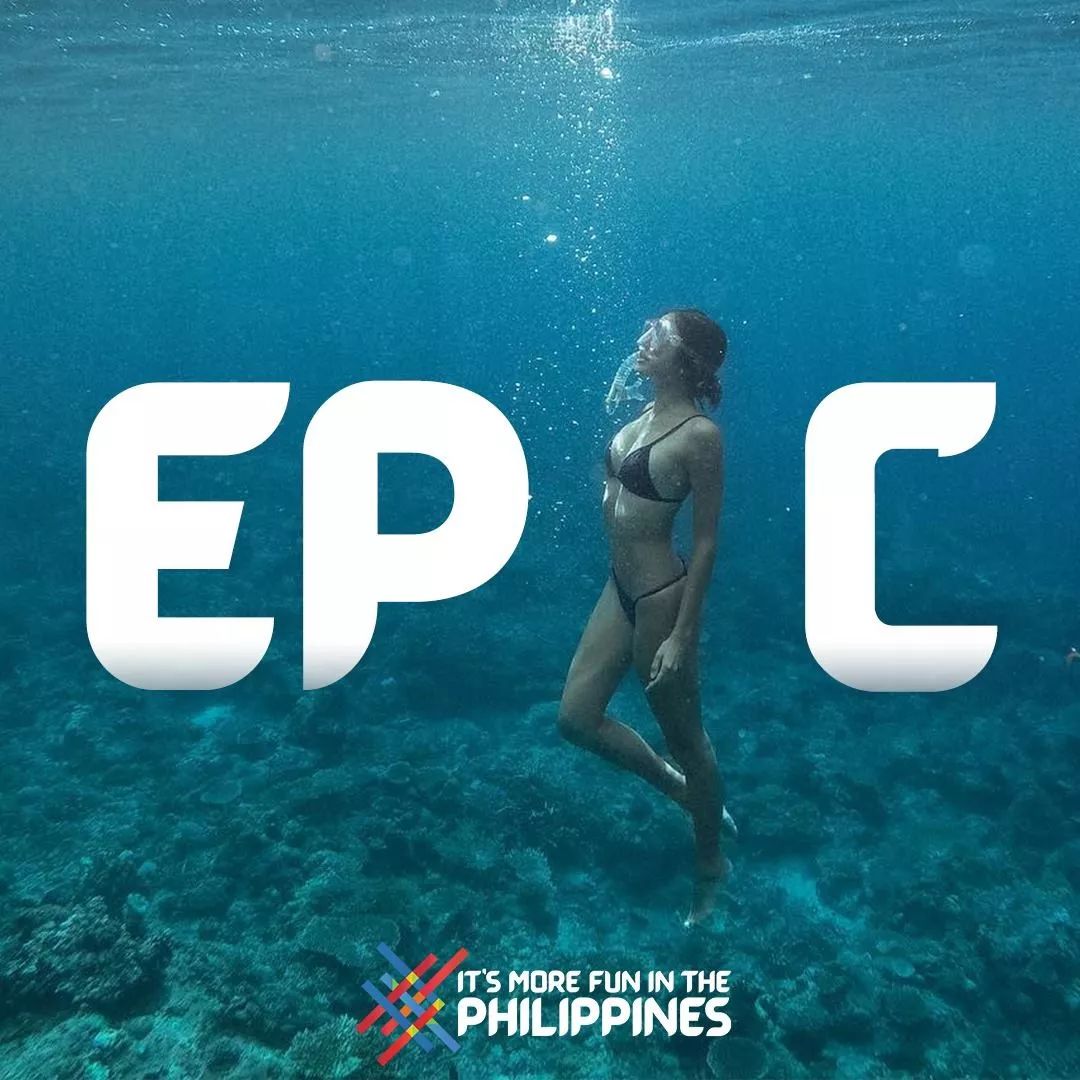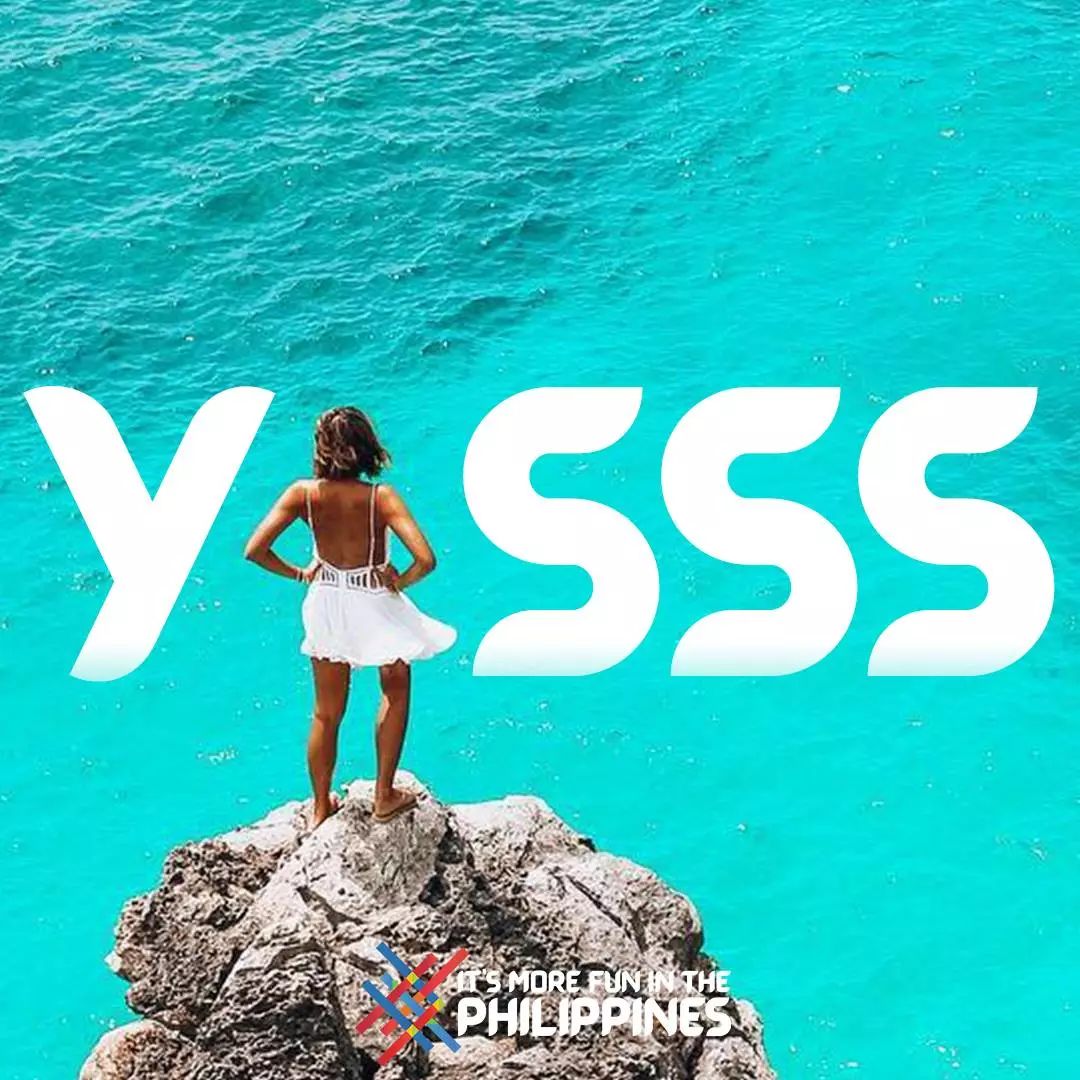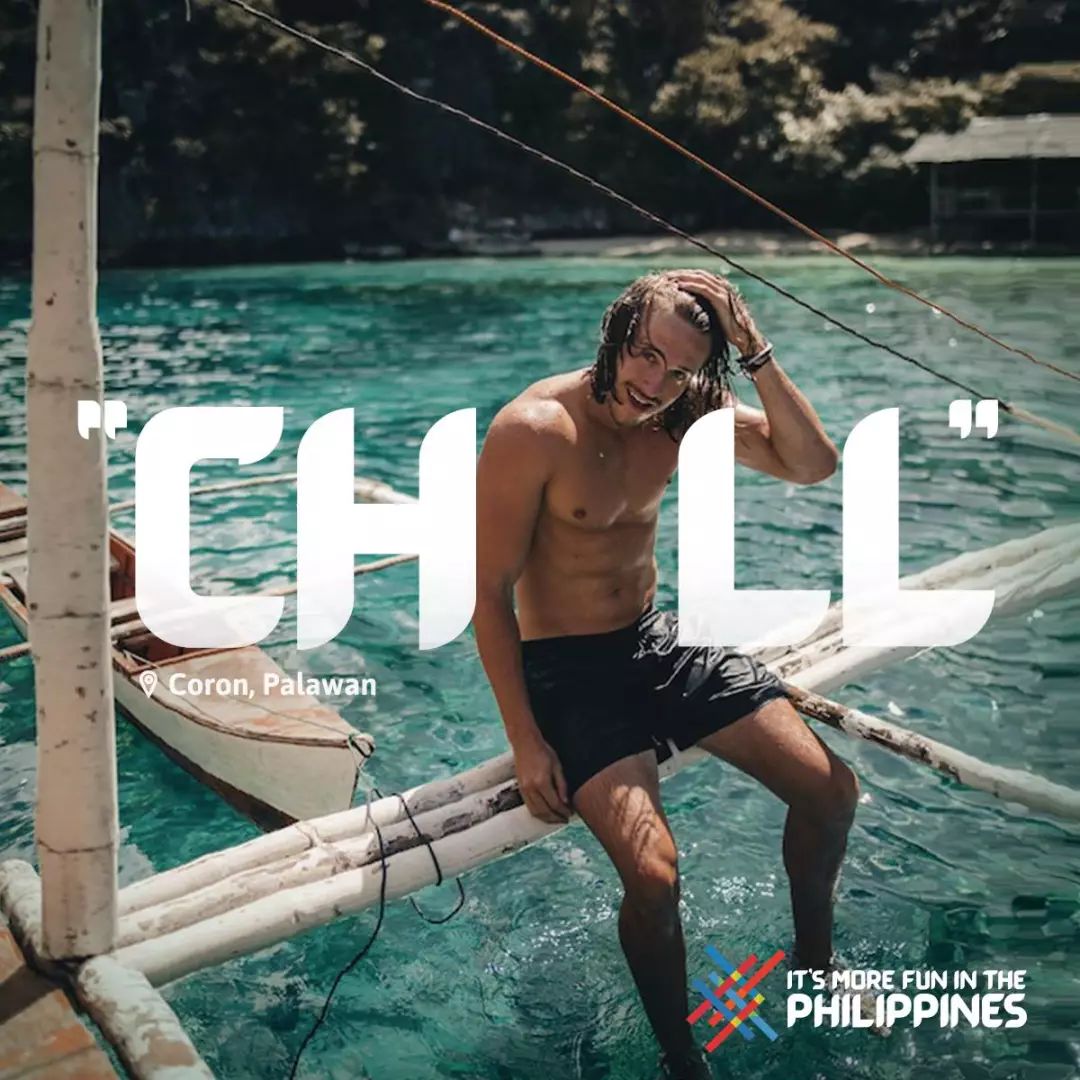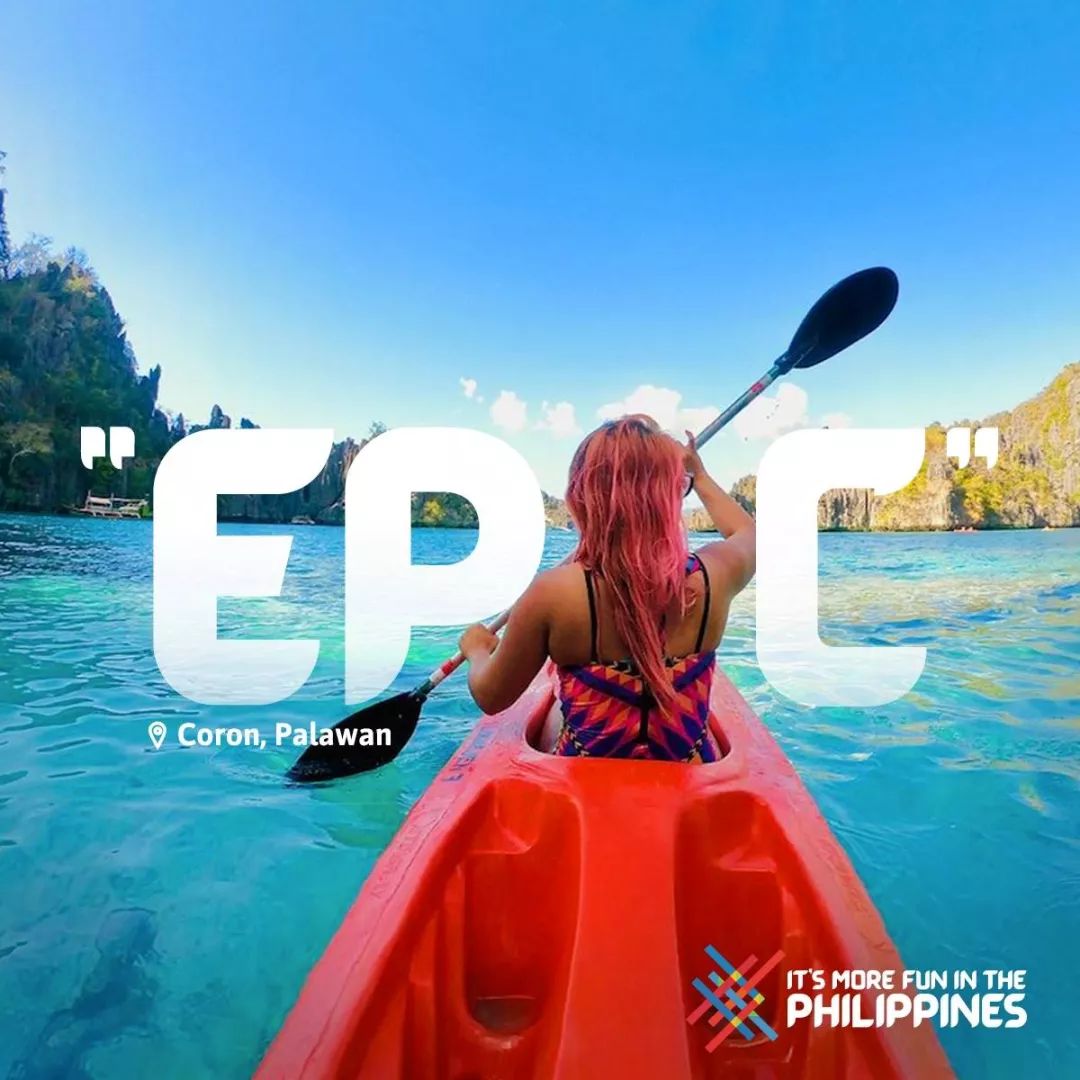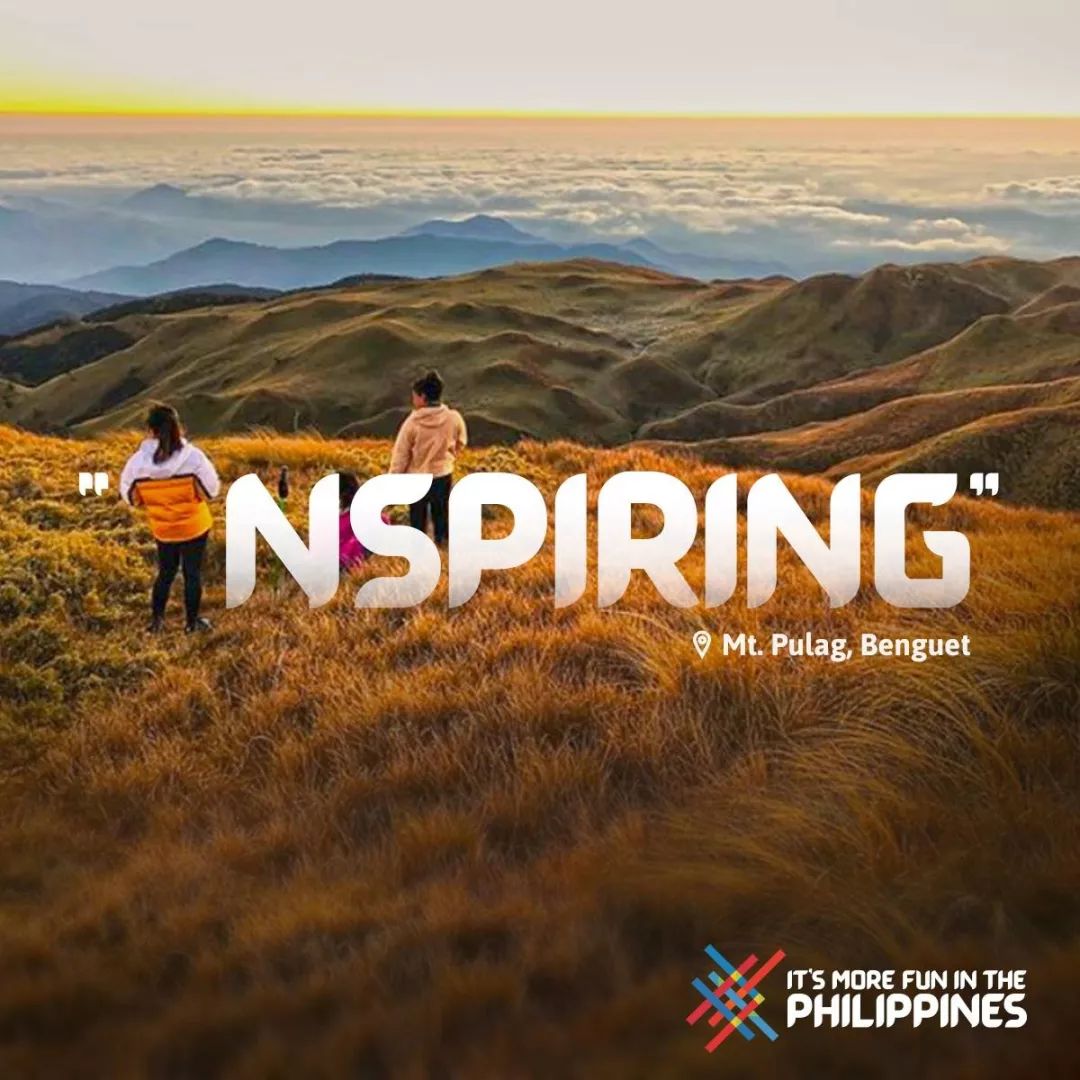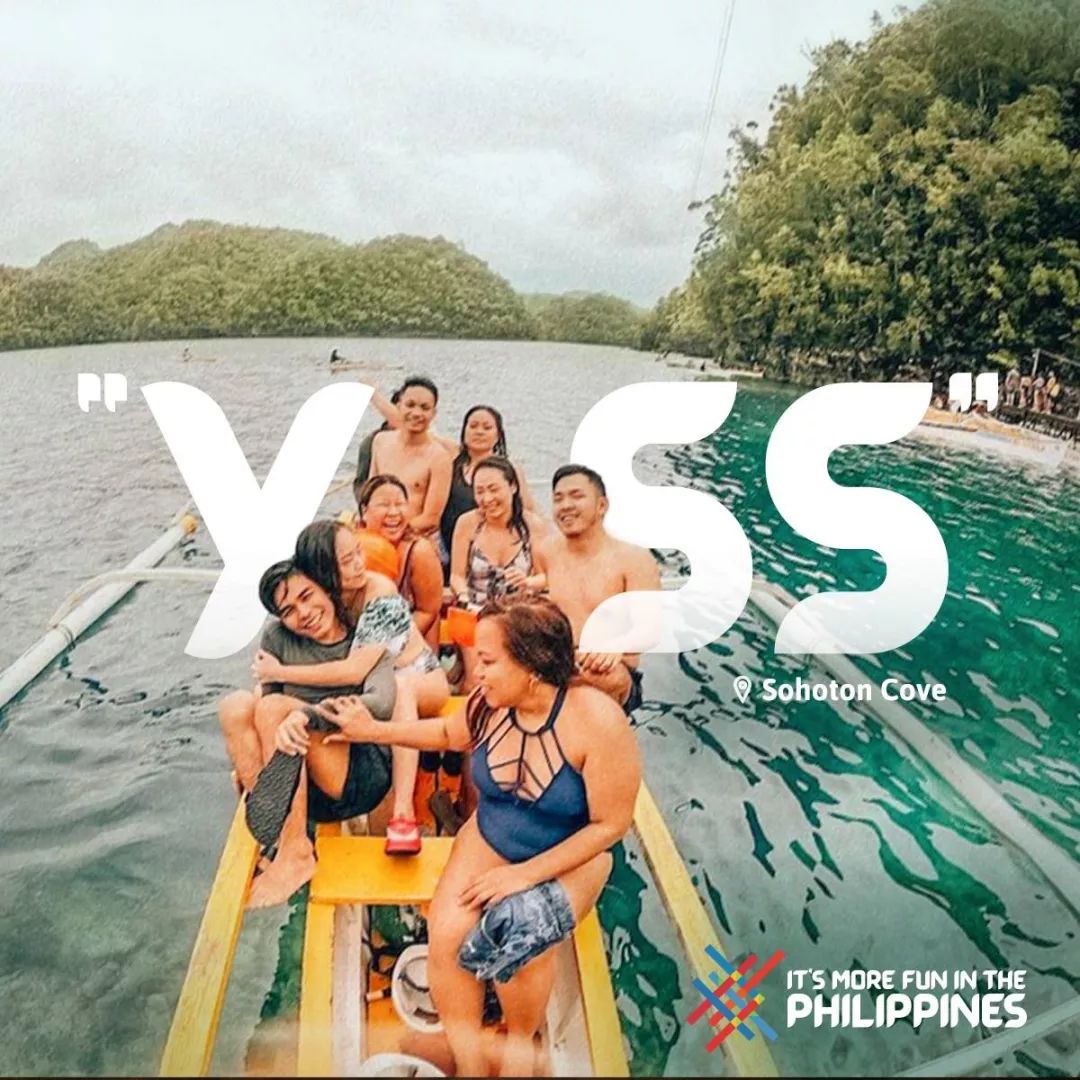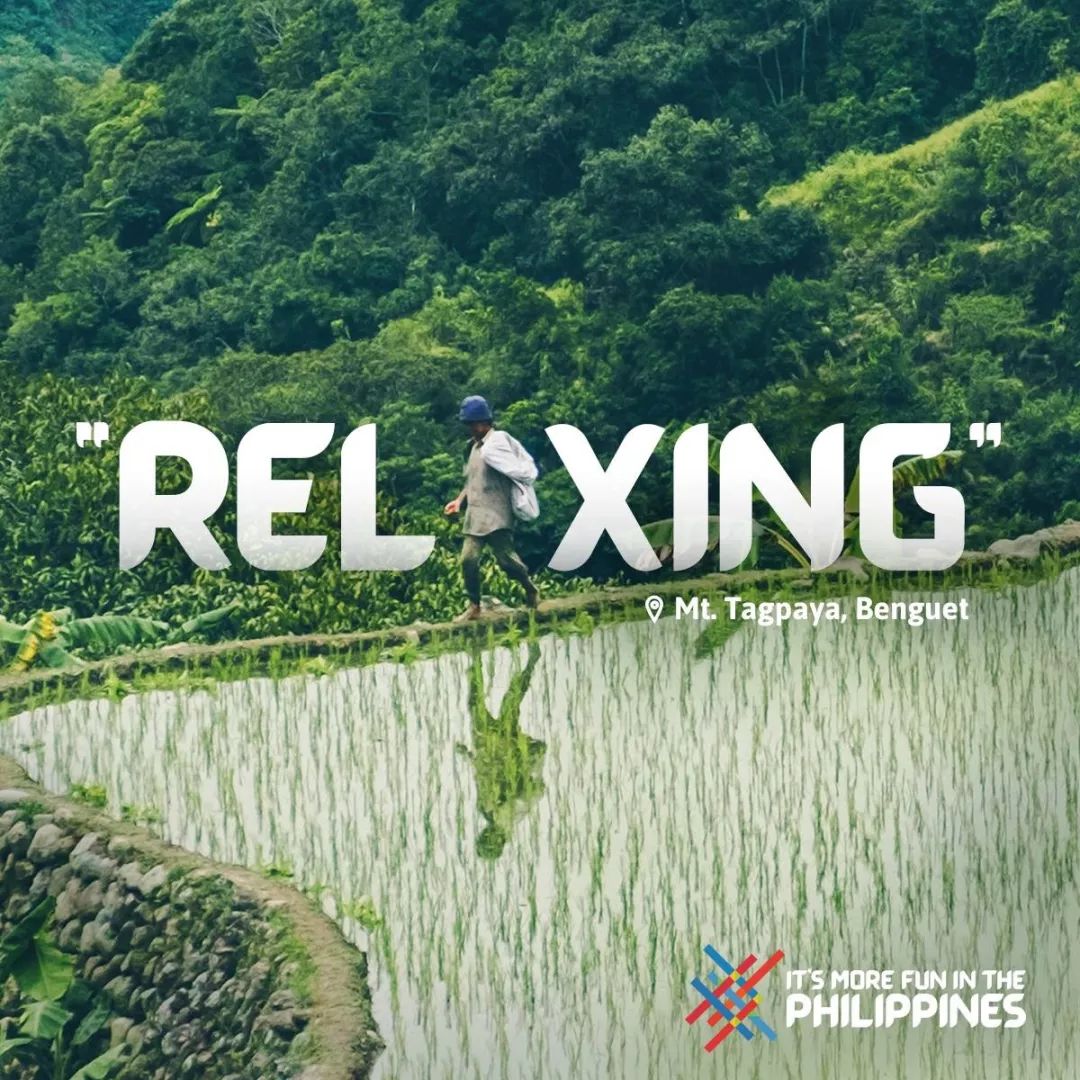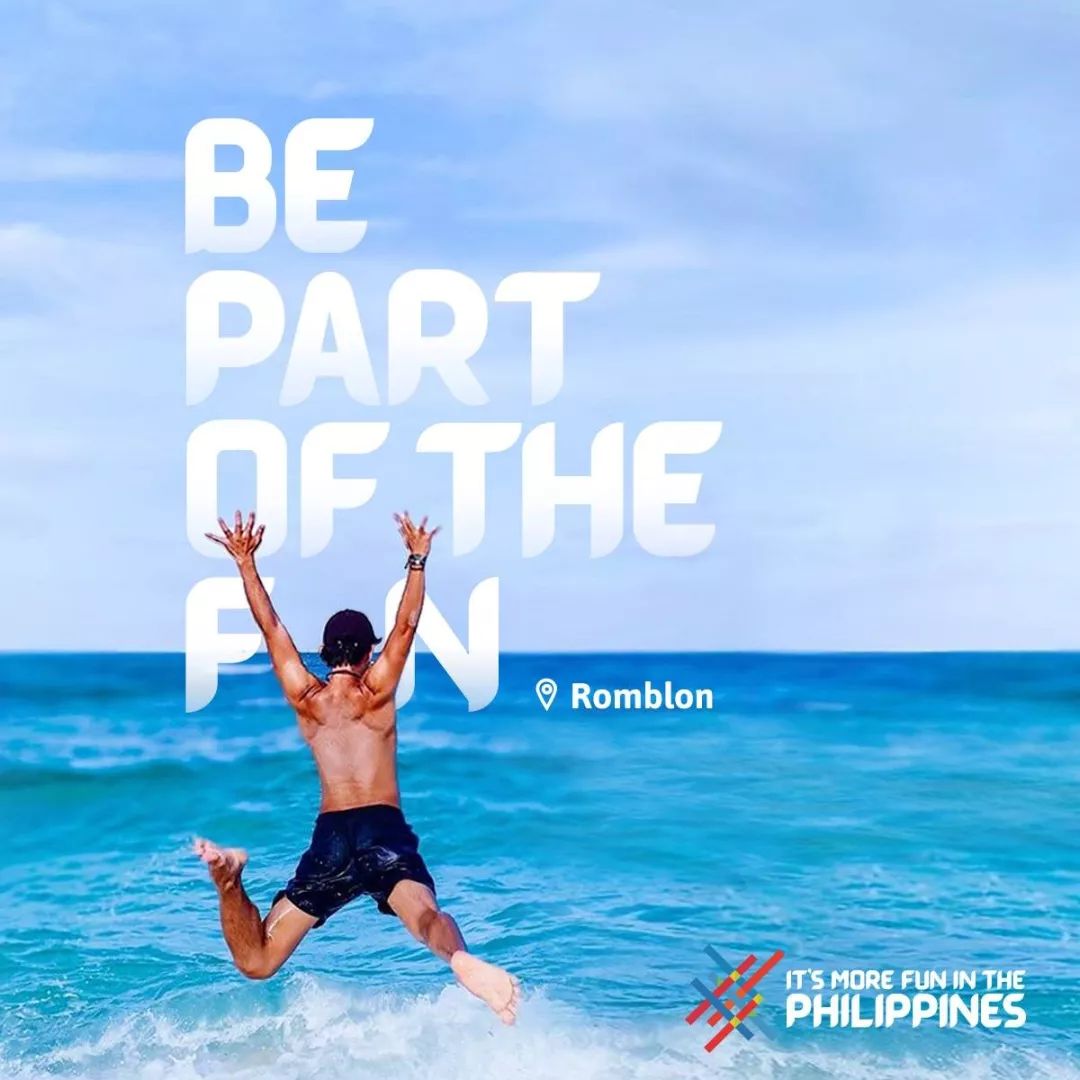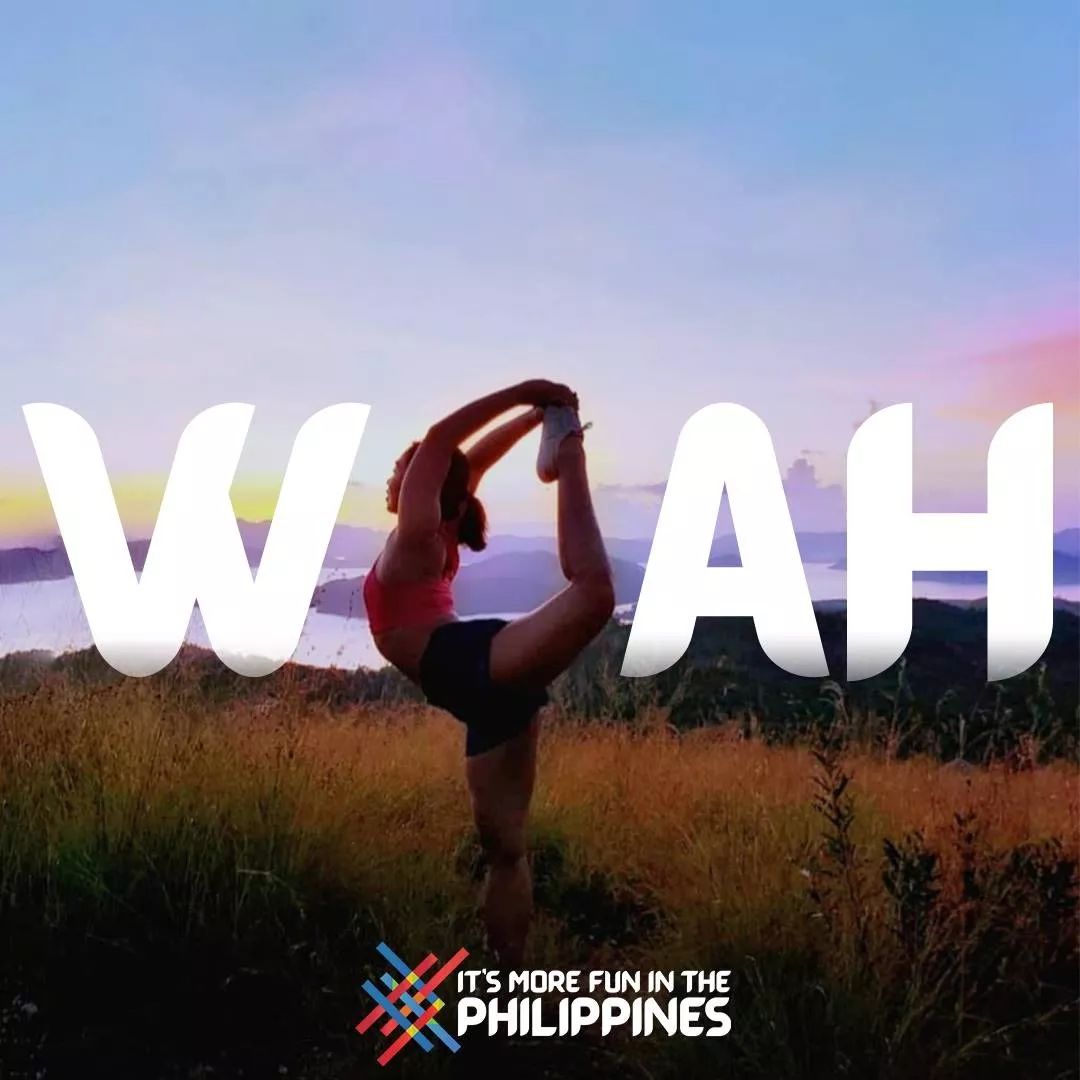
她设计了一套定制字体,让全球500万网友免费宣传!
“菲律宾更有趣!”(It’s More Fun in the Philippines)是2012年4月在菲律宾一次旅游活动中推出的新口号。
2019年2月18日,菲律宾旅游部(DOT)宣布重启“菲律宾更有趣!”这一口号,并采用了全新的LOGO。
新LOGO延续使用传统色彩和图案,并在原有的基础上进行了简化。新的配色取材于菲律宾传统编织、海洋、阳光、大梯田。
“菲律宾更有趣!”既是菲律宾的旅游品牌,同时也是一个应用程序,鼓励游客们发现菲律宾之美:游客在拍摄照片后与活动口号“菲律宾更有趣”定制叠加后,分享到Facebook、Instagram、Twitter等社交媒体。
此次品牌重塑,最明显的变化之一是广告中的新字体——一套名为“Barabara”的定制字体(custom typeface)。与2012年使用的无衬线字体“Harabara”不同,新字体的特色是从菲律宾标识牌中获取灵感,其名称“Barabara”既有本地特色,又延续了老名称的一部分。
推出新字体的想法来自菲律宾的广告代理商BBDO Guerrero,该公司赢得了新广告系列的竞标。
“旅游部的目标是重塑品牌。因此,我们首先考虑重新设计LOGO和字体,原始字体——Harabara由巴西设计师制作的,而现在的字体是由菲律宾本土设计师制作,字体灵感也来自本土——菲律宾的手绘标识牌。“BBDO艺术总监Michelle Co告诉Esquire。
正是Michelle Co,这位25岁的艺术总监为该品牌定制了字体,她说这种字体的灵感来自于吉普、三轮和海滩度假胜地上的手绘标牌,即使在最偏远的岛屿,这种手绘标牌仍然存在。带着这种标牌审美,结合好字体的设计元素,产生了一种新的无衬线(sans serif)字体。这种字体奇妙的地方在于,即使在屏幕上看,它也像手工制作出来的。
“当我在设计的时候,我们设计团队使用的是现有字体。但我觉得,菲律宾一直都有着独一无二的东西,我认为其他国家不具备我们所拥有的风格、味道和艺术,菲律宾应该有自己的样式、自己的味道,所以我们制作了一套富有国家个性的定制字体。“Co解释道。
Barabara除了拥有完整的英文字母,还带有印度-阿拉伯(Hindu-Arabic)数字的大写字母。根据Co的说法,最终设计甚至包括菲律宾比索(Peso)符号。
作为职业生涯早期具有纪念意义的项目,Co为她和她的团队所做的工作感到骄傲。
重启活动的核心目标之一,是通过本地和国际游客的分享,使这个国家成为一个“有趣”的旅游地。因此,菲律宾旅游部开放Barabara字体供大家下载,以鼓励菲律宾人在分享国家旅游照片或视频时使用这种字体,甚至欢迎在为企业设计宣传资料时也用它。
我们来欣赏一组网友嗨翻天的分享图吧!
我们最后看一下旧LOGO,旧LOGO图形非常复杂,源自菲律宾传统编织的样式里包含了菲律宾地图,每一种颜色代表着菲律宾的特色。
旧口号分两个版本,国内版为“菲律宾最有趣”(#1 for Fun Philippines),国际版为“菲律宾更有趣!”(It’s More Fun in the Philippines)。